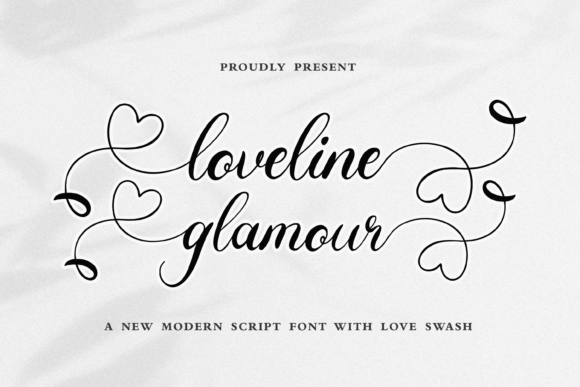
Loveline Glamour
Jika anda sedang mencari aset berkualiti tinggi seperti Loveline Glamour, pakej premium ini merupakan pilihan yang hebat untuk projek kreatif anda.
Sama ada anda mencipta produk POD (Print on Demand), jemputan perkahwinan atau grafik media sosial, Loveline Glamour amat bersesuaian.